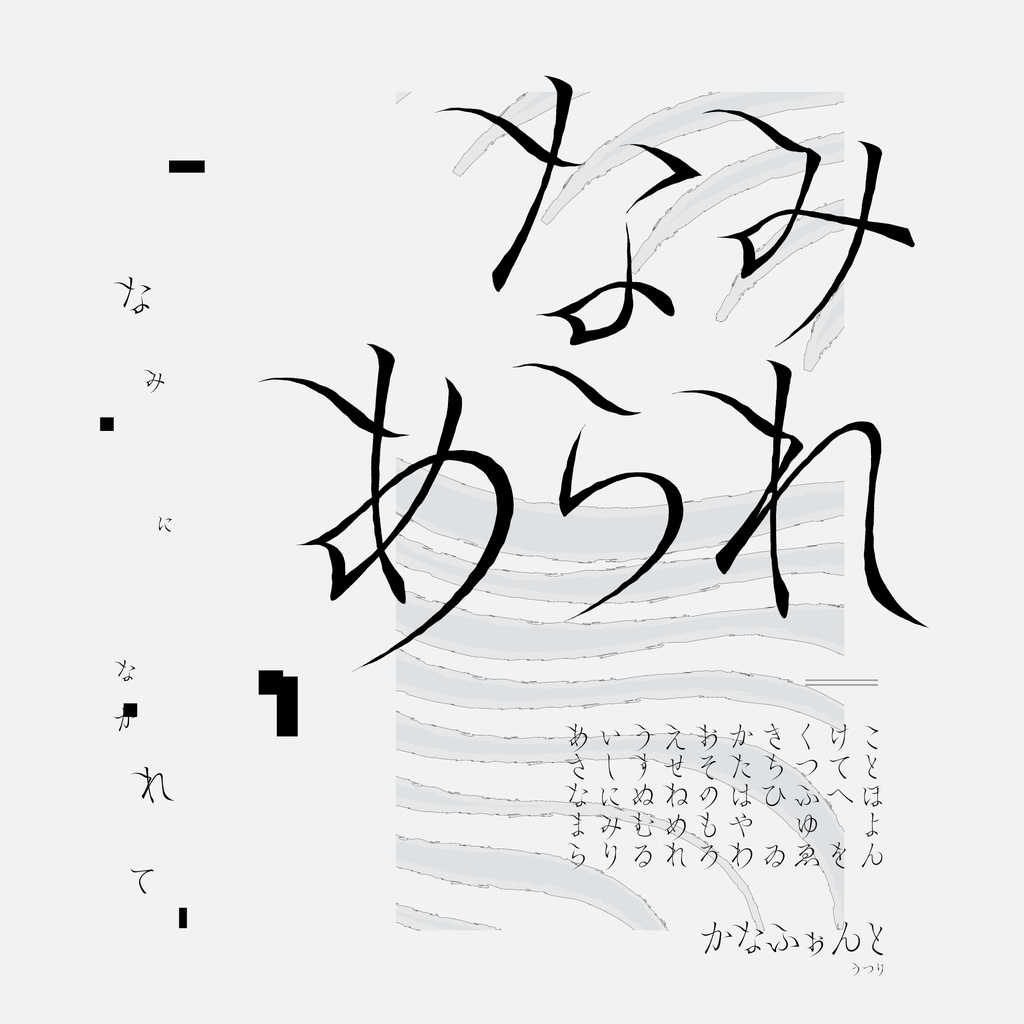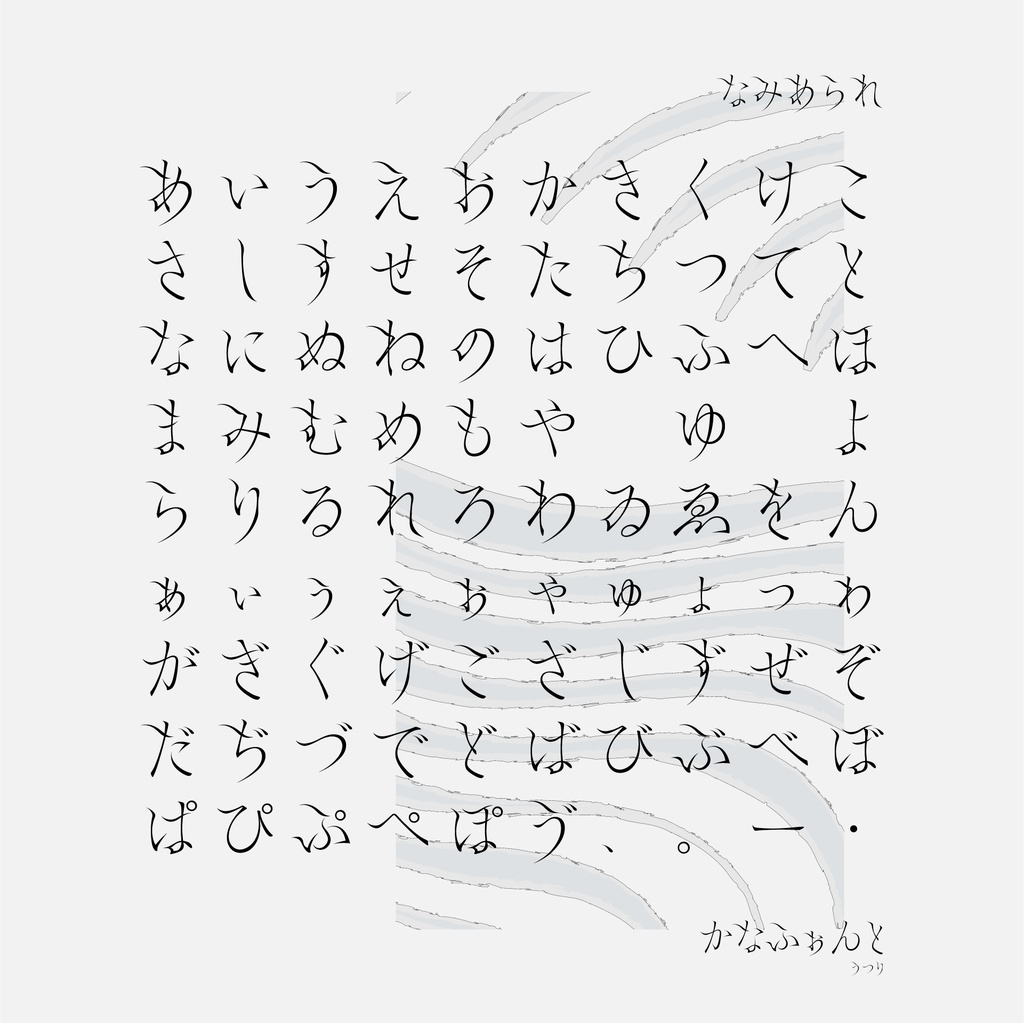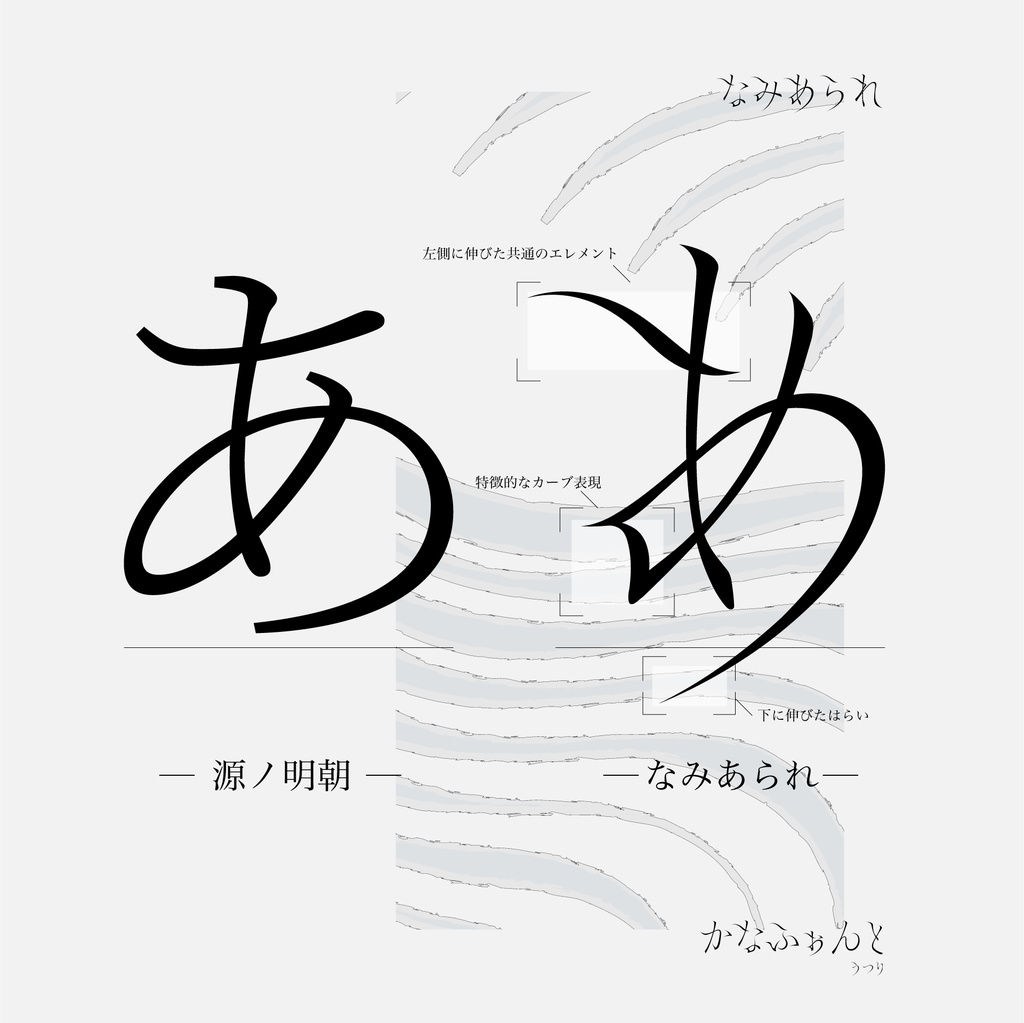
『なみあられ』 かなフォント
日本語かなフォント『なみあられ』 波のように流れるデザインを取り入れたひらがなフォントです。 【2026.04.10更新】 ■データ形式 OpenType ■収録文字 収録文字数90字。 あぁいぃうぅえぇおぉかがきぎくぐけげこごさざしじすずせぜそぞただちぢつっづてでとどなにぬねのはばぱひびぴふぶぷへべぺほぼぽまみむめもやゃゆゅよょらりるれろわゎゐゑをんゔ、。ー・゛゜ ■ライセンス 1ライセンスにつき、1ユーザー1PCの範囲で利用可能です。 個人・法人を問わず、私用・商用に関わらず利用可能です。 クレジットの表記や利用報告は必要ありません。 ■免責事項 商品の性質上、返品および返金対応は致しかねます。 本フォントは予告なくアップデート、または配布を停止する場合があります。 ■禁止事項 以下の行為は禁止とさせていただきます。 ・本フォントファイルの無断での二次配布、譲渡、販売。 ・本フォントのデータの一部または全部を改変し、新たなフォントとして公開・販売すること。 ・公序良俗に反する目的、誹謗中傷、違法行為に関わるコンテンツでの使用 *上記内容は予告なく変更する場合がございます。あらかじめご了承ください。